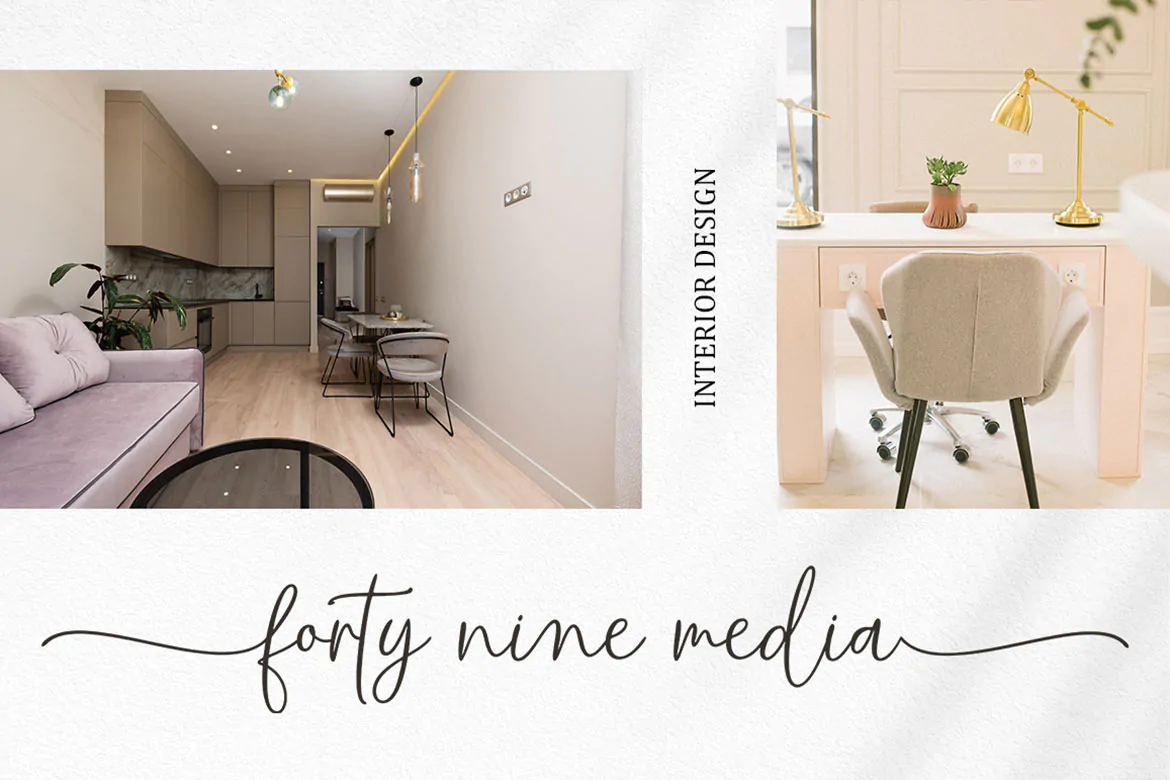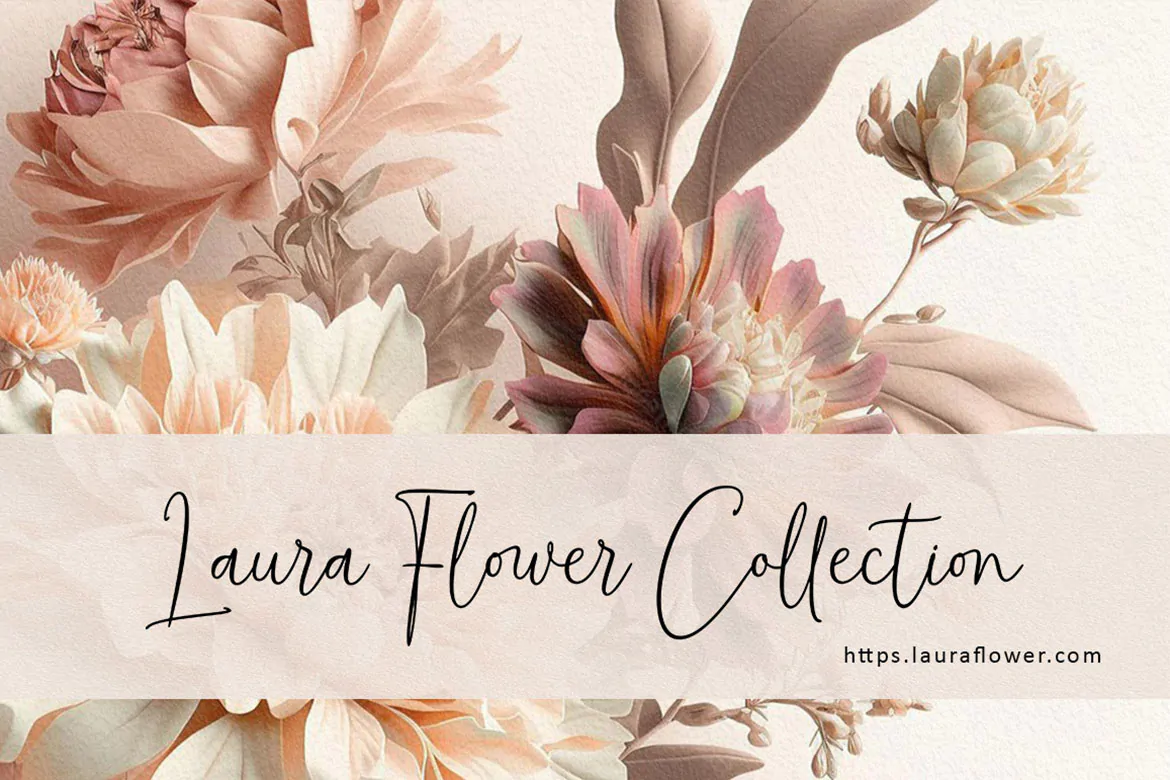
فونت امضا دستنویس Shelling
فونت امضا دستنویس
فونت امضا دستنویس Shelling یک اسکریپت فونت فوق العاده زیبا است که میتوانید از آن در طراحی بسته بندی محصولات، کاور آلبوم موسیقی، آرایشی و بهداشتی، پوستر، برشور و دیگر پروژههای گرافیکی استفاده کنید.